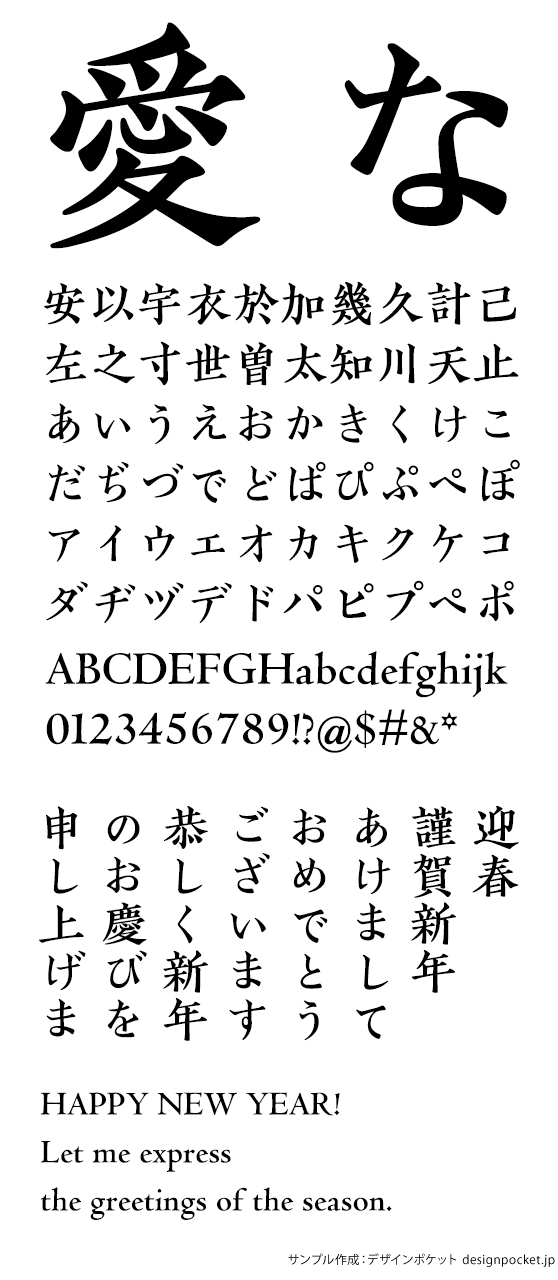
宋朝体
KOひふみ陳起B
KOHifumiChinki-B
『神字日文伝』(平田篤胤著、1824)から翻刻した「ひふみ」に、『南宋羣賢小集』(陳宅書籍鋪、1208—1264)にもちいられた字様をもとに翻刻した臨安宋朝体「陳起」、ニコラ・ジェンソンの活字を使用したプリニウス著『博物誌』(1472)から復刻したヴェネチアン・ローマン体「K.E.Aries」を組み合わせた「KOひふみ陳起M」のファミリーで、ボールド・ウエイトです。
KOひふみ陳起B